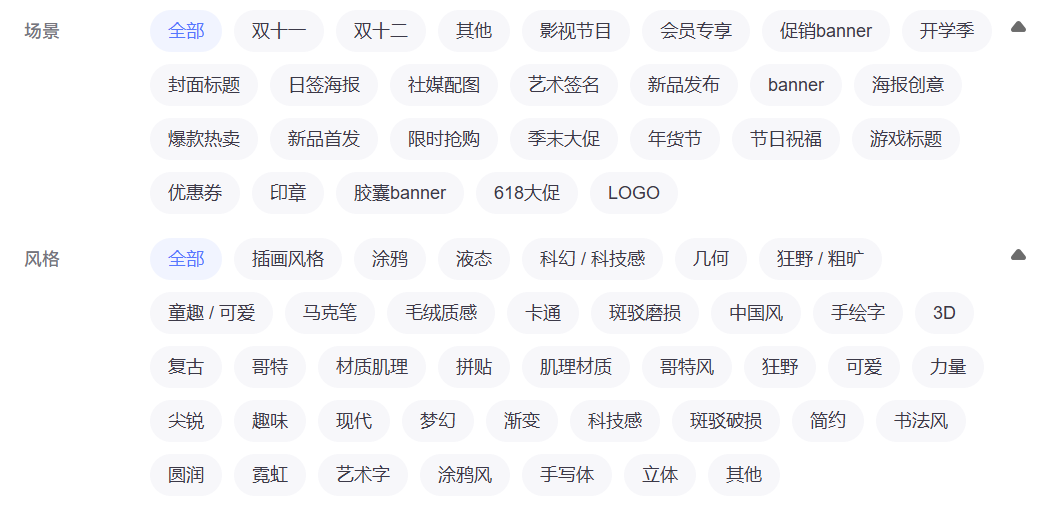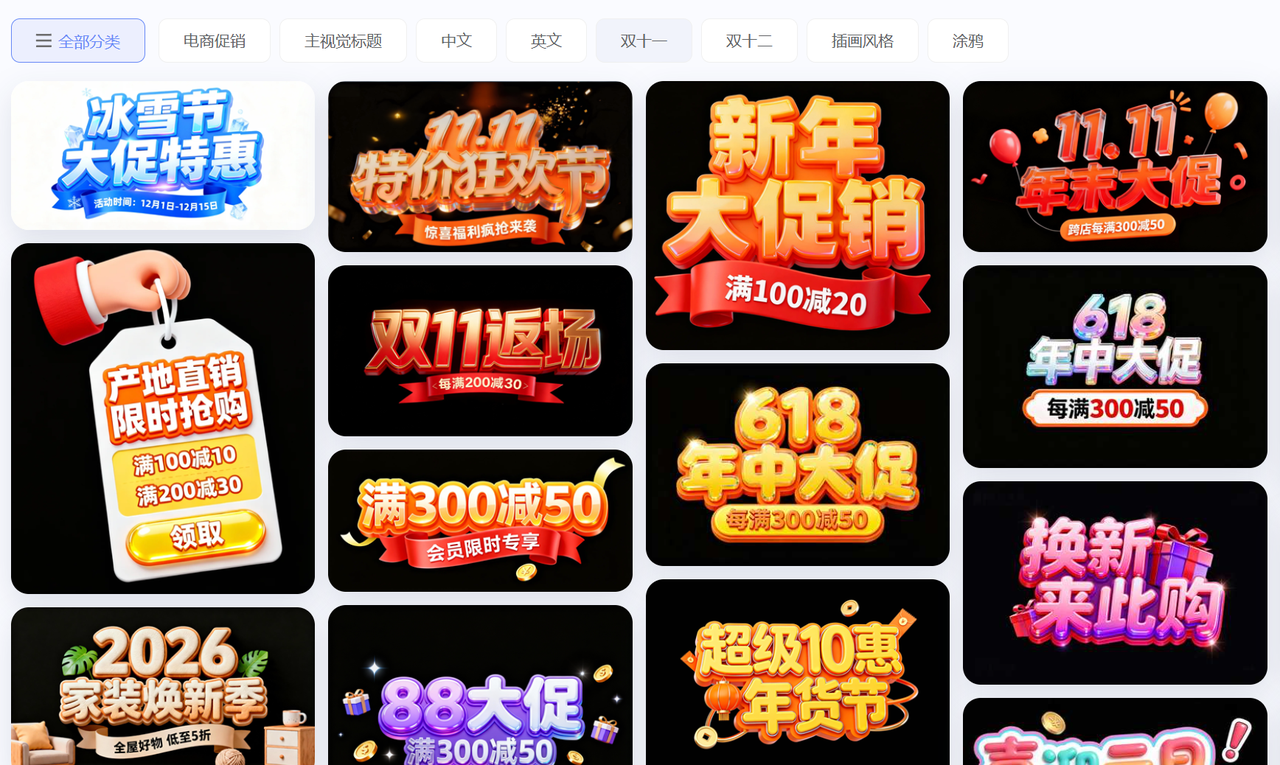
4 款强大实用的 AI 生成字体的工具推荐
最近两年 AI 生成领域发展非常快,从 AI 生图到 AI 生成视频、音乐,AI 好像无所不能。我曾经也在想 AI 生成字体这个场景是否能够实现,本文就给大家介绍一些可以 AI 生成字体的工具。
本文给大家介绍的 AI 生成字体,并不是利用 AI 生成一整套像“思源黑体”一样的字体库,而是用 AI 来生成自己喜欢的字体文字,省去大家去找字体的时间,更主要的 AI 生成的字体是免费商用。接下来我就来给大家推荐几款我觉得非常实用的 AI 生成字体的工具。
我们都知道字由是一款非常好用的字体下载和管理工具,同时字由也有非常好用字体 AI 功能,比如最近上线的【AI 工具】功能,提供非常丰富的字体模板,只需要替换文字,就可以生成同样效果的字体素材。
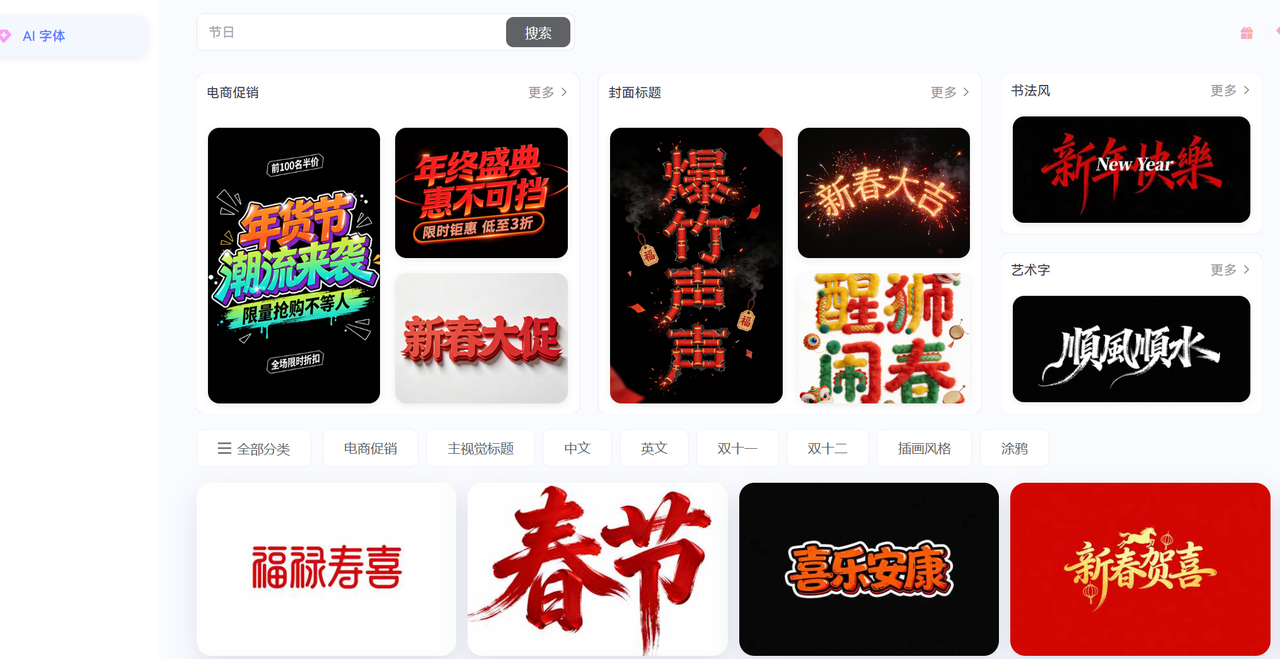
可以通过常见和风格筛选,快速查找自己想要的艺术字体。
比如我们需要一个年底促销的字体素材,我们可以按照下面的步骤进行生成
1、在场景分类中找到“年货节”,我们可以看到非常丰富的模板就出来了
2、选择一个喜欢的模板,点击进去,输入自己的文案,点击“立即生成”,即可一键生成对应字体
Midjourney
Midjourney 它不是专门的“字体生成器”,但这个强大的 AI 图像生成工具在字体设计领域扮演着越来越重要的角色,尤其是在艺术字生成方面。你只需要输入一些描述性词语,它就能为你呈现出各种令人惊艳的视觉效果,其中就包括了风格独特的字体设计。同样的工具还有 DALL-E, Stable Diffusion 等大模型。
这些工具的核心原理是基于大规模的图像和文本数据进行训练,从而能够理解并生成与 Prompt 提示词相关的图像。它们能够模拟各种艺术风格、材质、光影效果。对于字体设计而言,这意味着你可以描述你想要的字体风格,比如“赛博朋克风格的中文宋体”、“未来主义的英文手写体”、“古朴典雅的篆刻字体”等等,在生成设计的同时,直接生成想要的字体风格。
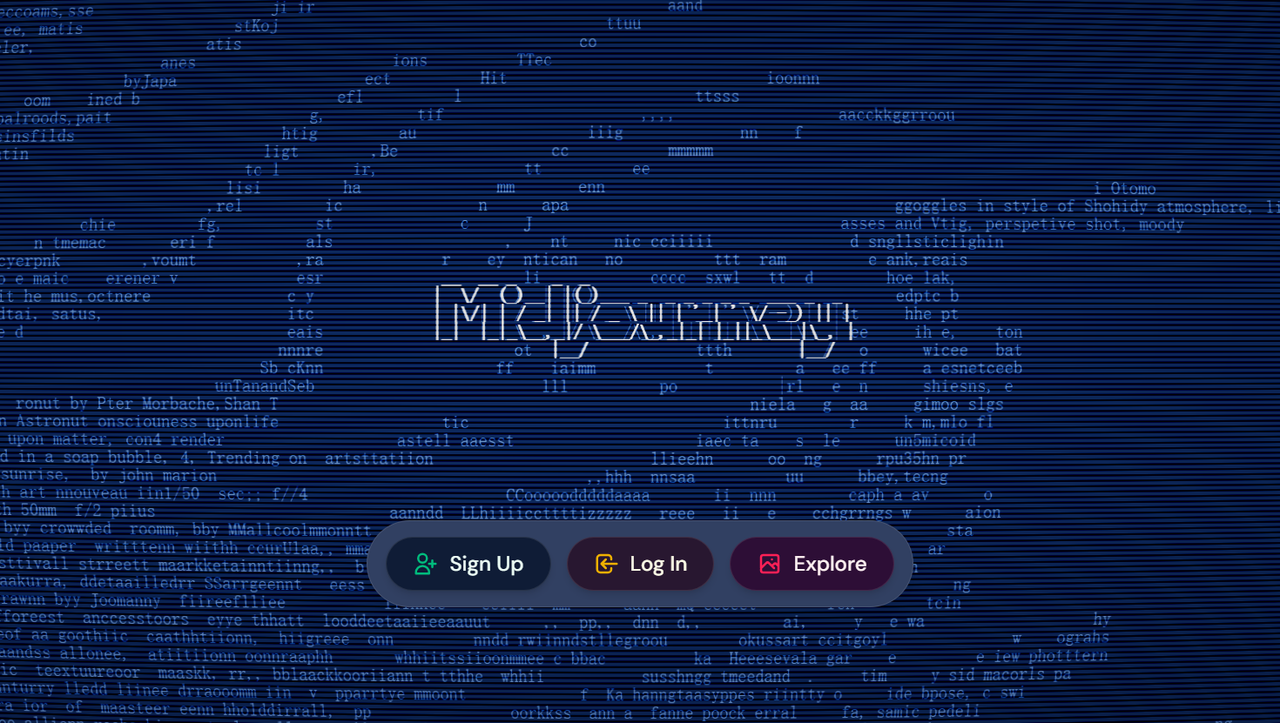
Fontjoy
这款软件也不是生成一个新的字体库或者字体风格,它可以生成搭配的字体,或者说匹配更合适一些。
对于一套完整的视觉设计方案来说,只拥有一个漂亮的字体是不够的,你还需要其他字体来配合标题、正文、辅助信息等,而这些字体之间必须和谐共存,共同营造出统一的视觉风格。Fontjoy正是利用AI来帮助你找到最佳的字体组合。
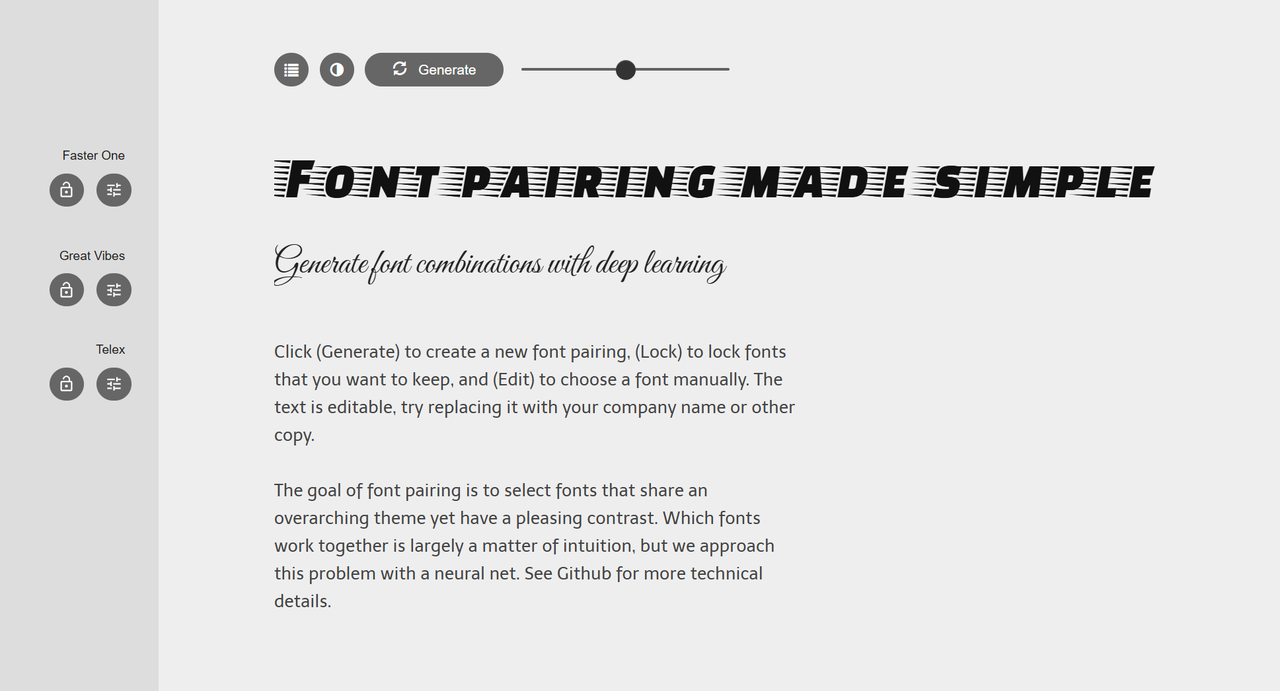
它的核心功能是利用机器学习算法,根据你选择的一个基础字体,智能推荐出与之搭配和谐的其他字体。这是它的核心卖点。你只需点击“Generate”按钮,它就会随机生成匹配的字体组合。它不仅仅是随机推荐,而是基于对字体美学和排版原则的深刻理解来给出建议。例如,它可能会推荐一个粗衬线体作为标题,搭配一个纤细的无衬线体作为正文,以达到视觉上的平衡和信息层级的分明。
Adobe Illustrator
Adobe作为创意软件的巨头,自然不会错过AI这波浪潮。虽然Illustrator目前还没有一个一键生成完整字体的功能,但它集成的生成式AI功能,如“文本转矢量图形”(Text to Vector Graphic)已经为字体设计师提供了强大的辅助,尤其是在单个字母或局部字形设计以及字体艺术效果处理方面。
文本转矢量图形这是一个非常酷的功能。你可以输入一段描述性的文本提示,比如“一个由藤蔓编织而成的字母A”、“一个带有蒸汽朋克风格齿轮元素的字母M”,AI就会根据你的描述,生成相应的矢量图形。这些图形可以是单个字母,也可以是更复杂的图案。虽然它不能一次性生成整套字体,但你可以用它来设计特定的艺术字标题、Logo中的字母元素,或者为一套字体中的某个特殊字符提供创意。
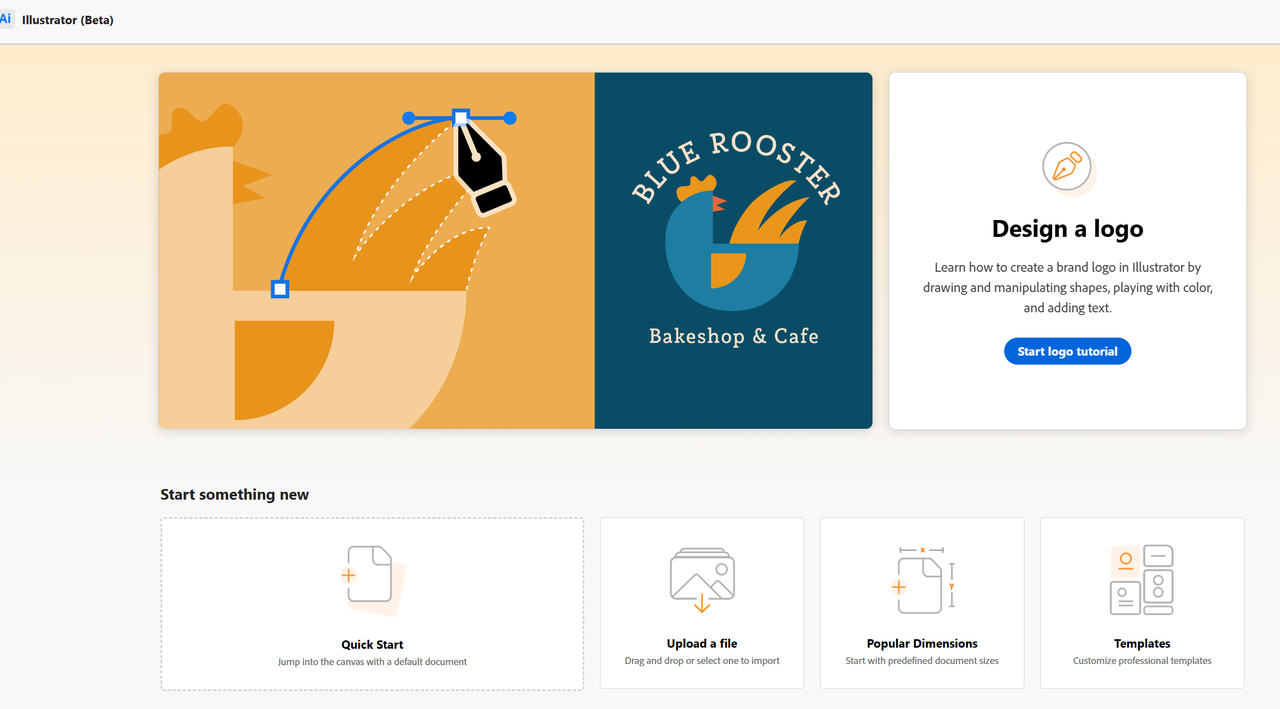
总结与选择建议
AI在字体设计领域的应用,还处于比较早期的阶段,但毫无疑问,它已经能帮你拓宽思路,提高效率,甚至实现一些原本难以想象的创意。比如字由利用模板生成艺术字体的功能就非常实用,大家可以多去尝试和使用。